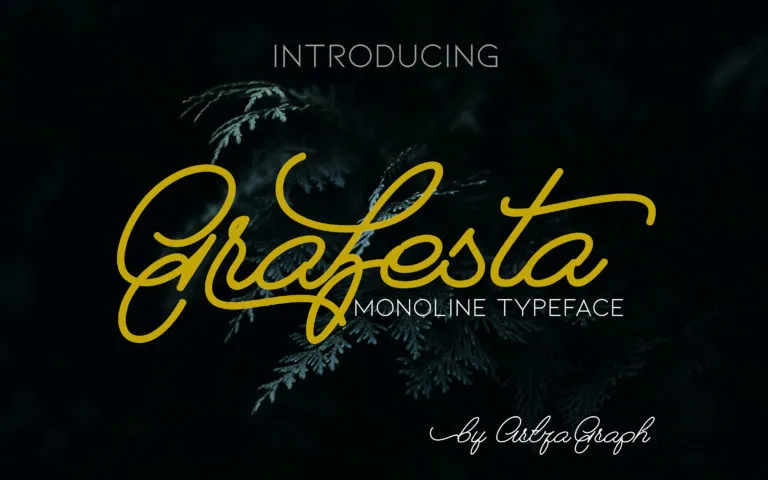
Grafesta Monoline Script Font – Fonte Grátis
Grafesta Monoline Script Font
Introduzimos a Grafesta Font, uma nova coleção de Tipografia Script Monoline do Artza Graph. Com origem na tipografia coperplate e evoluindo até ao contemporâneo, esta font se destaca pela sua elegância natural, beleza clássica e toque suave. A Grafesta é um script de estilo monoline elegantemente cuidadoso, projetado para uma variedade de projetos estilizados. Estando repleto de uma característica natural que permite a personalização para diversos tipos de projeto moderno e sofisticado, a Grafesta se torna perfeita para diversas aplicações como criação de marcas, logotipos, designs de casamento, posts nas redes sociais, anúncios, embalagens, design de produtos, selos, fotografia, marca d’água, convites e materiais de escritório. Ela também se destaca para qualquer aplicação que necessite da sua autêntica tonalidade de escrita manual. Esta font não apenas oferece um toque suave e elegante ao seu projeto, mas também é capaz de adaptar-se a uma variedade impressionante de projetos estilizados, tornando-a um recurso indispensável para qualquer designer em busca de criar designs sofisticados e criativos.